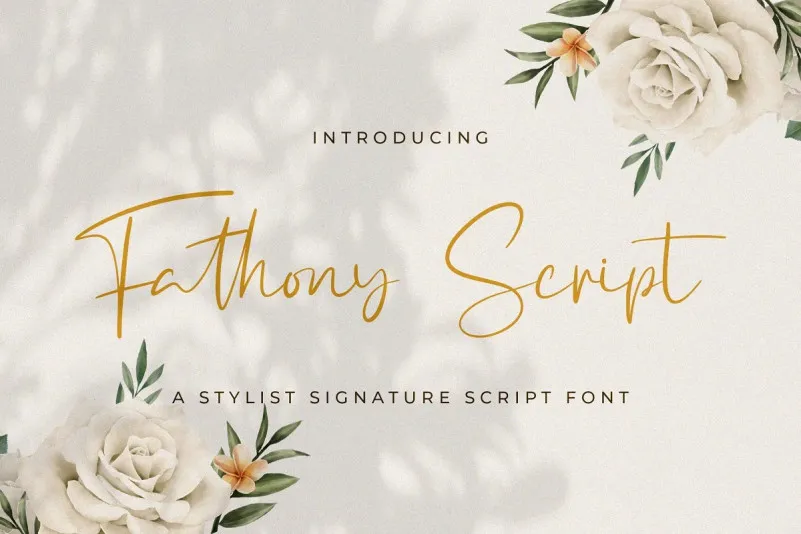
Fathony Script Font – Fonte Grátis
Fathony Script Font
Fathony Script é uma fonte script criada por StringLabs com uma aparência autêntica e moderna que remete à arte do traçado a mão. Esta elegante fonte, cuidadosamente balanceada, se destaca não apenas como uma opção de branding, mas também para projetos digitais onde um toque delicado é essencial. A Fathony Script oferece uma versatilidade impressionante, capaz de combinar perfeitamente com uma ampla variedade de design. Seja você um estilista digital que busca trazer vida aos seus projetos criativos ou alguém procurando por uma fonte para suas campanhas de branding, essa fonte é uma ótima opção. Com seu olhar moderno e chamado a ser utilizado em qualquer projeto exigente, Fathony Script não decepciona. Experimentar a integração desta fonte no seu próximo trabalho irá fazer toda a diferença, levando seus projetos para um nível mais alto.